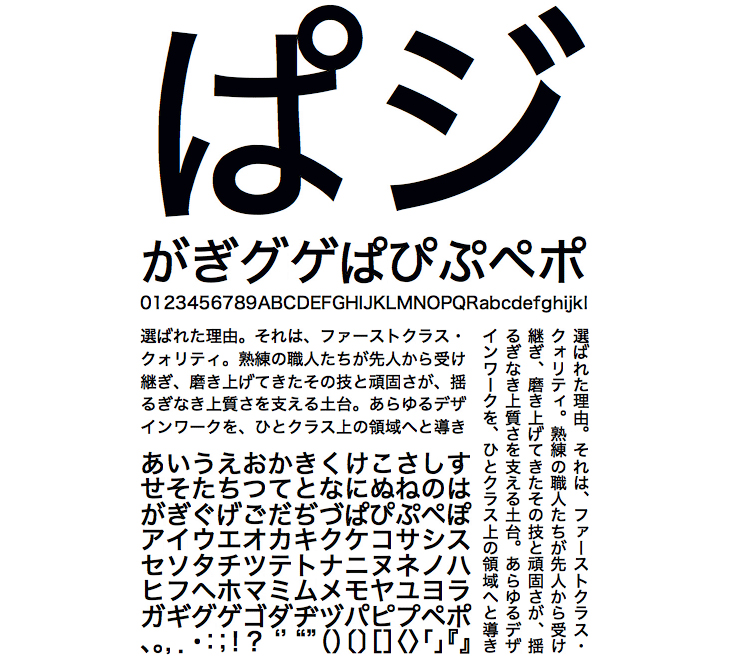
仮名・英数字グリフのみ収容
※本商品は仮名書体です。ギャラリーの見本に含まれる漢字はヒラギノ角ゴを使用しています。
【ヒラギノ角Pack仮名】パッケージの注意書きや地図など、小サイズの文字を使用する場合に濁点・半濁点を判読しやすいように大きくして、視認性および可読性を高めた仮名書体です。濁点・半濁点を持つ文字以外は「ヒラギノ角ゴ」と同字形となります。
ヒラギノ角Pack仮名 W5